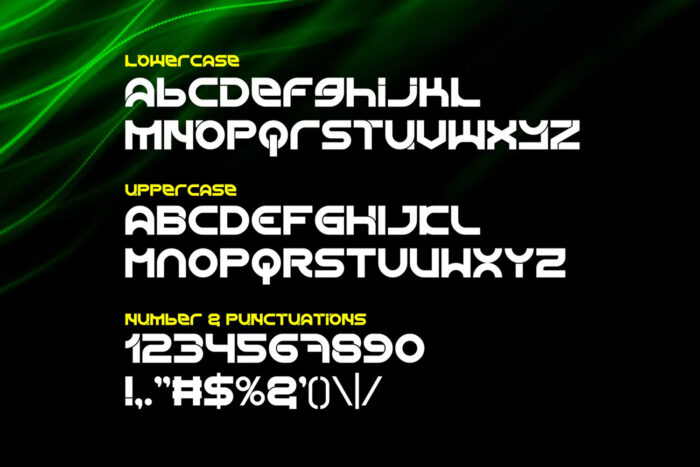
DVN Soda Việt hóa – Font chữ dành cho thiết kế năng động, logo
DVN Soda Việt hóa là một font chữ độc đáo và sáng tạo, lý tưởng cho các thiết kế năng động và logo. Font chữ này có đường nét mạnh mẽ và hiện đại, với các ký tự được thiết kế cân đối và gọn gàng. Các đường nét của font chữ thể hiện sự chắc chắn và cứng cáp, mang lại cảm giác năng động và tràn đầy năng lượng. Đặc biệt, các ký tự trong “DVN Soda Việt hóa” có sự pha trộn giữa các đường cong mềm mại và các góc cạnh sắc nét, tạo nên một phong cách độc đáo và ấn tượng.
Ứng dụng của font chữ rất đa dạng, phù hợp cho nhiều loại thiết kế khác nhau như logo, tiêu đề, poster, banner, và các dự án đồ họa cần sự nổi bật và thu hút. Với phong cách mạnh mẽ và hiện đại, font chữ này không chỉ giúp tạo nên những thiết kế bắt mắt mà còn giúp truyền tải thông điệp một cách rõ ràng và ấn tượng. “DVN Soda Việt hóa” chắc chắn sẽ là lựa chọn hoàn hảo cho các dự án thiết kế cần sự đột phá và sáng tạo.